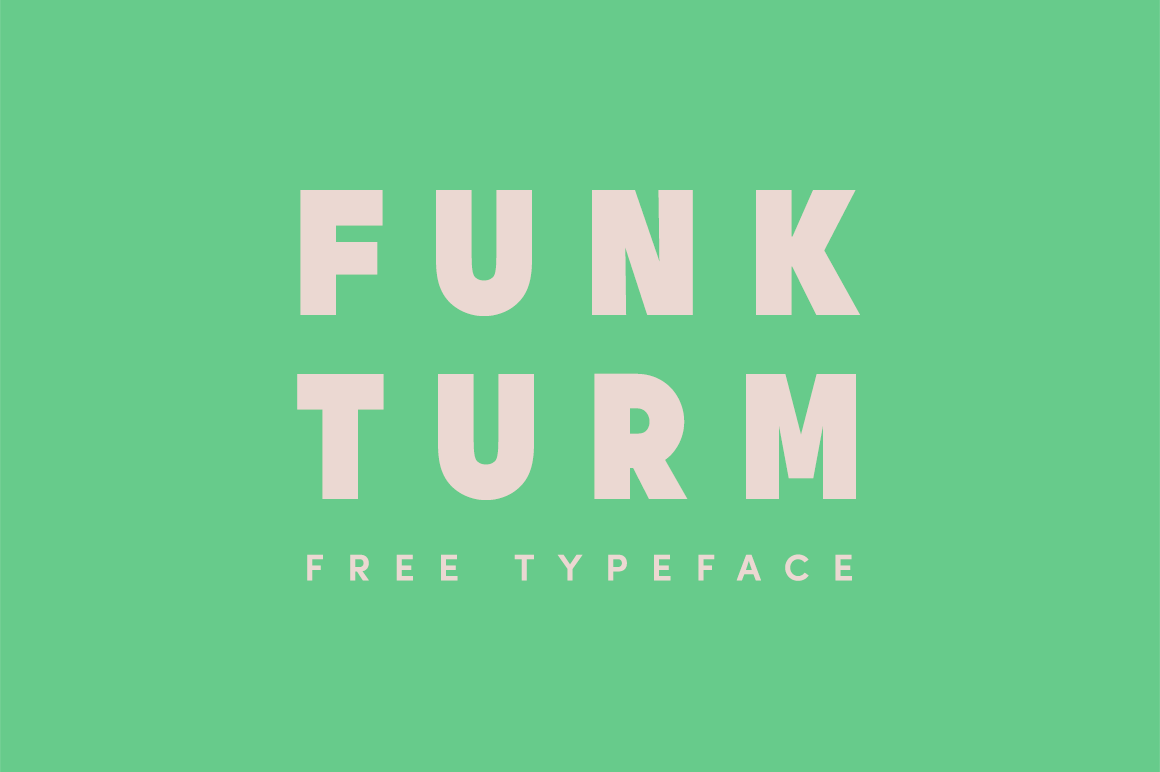
Funkturm Typeface – Fonte Grátis
Funkturm Typeface
A ‘Funkturm Typeface’ é uma escolha perfeita para aqueles que buscam um estilo moderno e dinâmico para suas criações digitais. Inspirada nas formas puras de tipo sans serif, essa fonte oferece uma aparência clean e minimalista que complementa perfeitamente qualquer design gráfico contemporâneo. Com a ‘Funkturm Typeface’, você pode criar textos chamativos e legíveis em uma variedade de ambientes digitais. Suas linhas retas e curvas simples, sem adornos frívolos, permitem um texto fluente e fácil de ler, tornando-a ideal para aplicações variadas como blogs, sites profissionais ou até mesmo gráficos publicitários. Além disso, a ‘Funkturm Typeface’ do designer ff2222 traz uma leve atmosfera descontraída que combina bem com temas atuais e modernos. Seja você um criador de conteúdo digital ou um profissional desejando dar vida à sua identidade visual, essa fonte é uma ótima opção para quem busca um estilo único que não se distancia dos padrões contemporâneos do design gráfico.